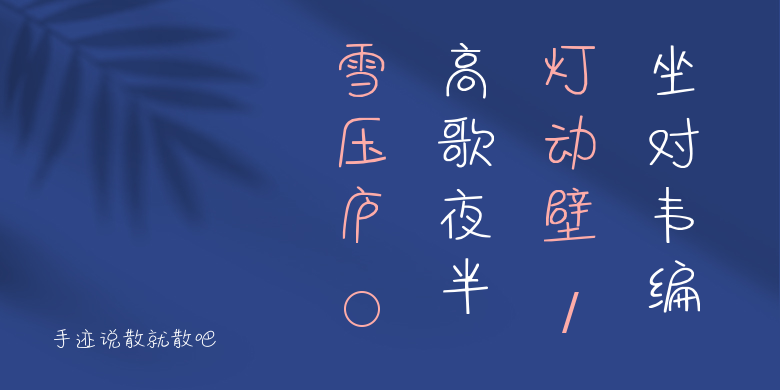
手迹说散就散吧
手迹说散就散吧,这款字体结构工整、笔画清晰,兼顾美观与易读性,适用于标题、正文、海报、包装、LOGO 等多种场景。字形优雅稳定,风格百搭耐看,适配日常排版与创意设计,让文字呈现更舒适、更具质感。手迹说散就散吧一笔一画,皆是细节,以均衡的比例、流畅的线条打造舒适视觉体验,字形端正大气,风格简约现代。无论是商业设计、品牌宣传还是日常排版,都能轻松驾驭,让文字更有格调与力量。手迹说散就散吧字体下载。